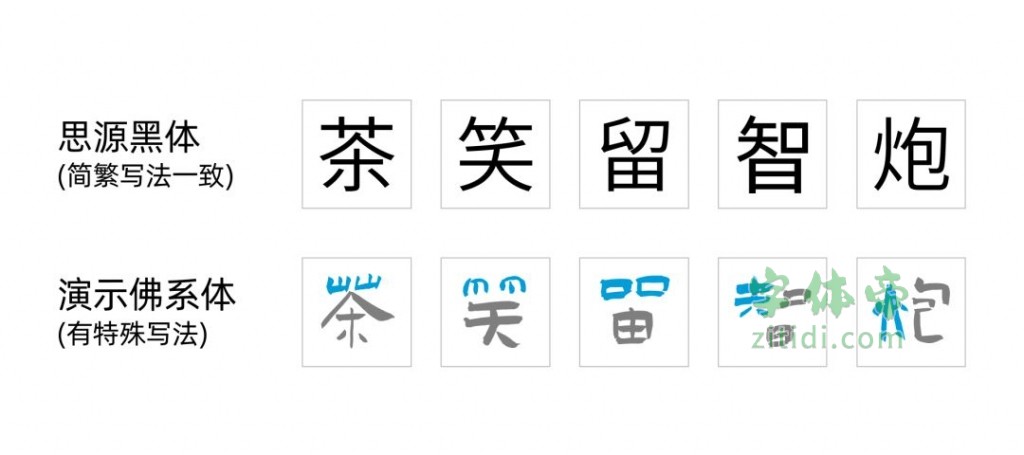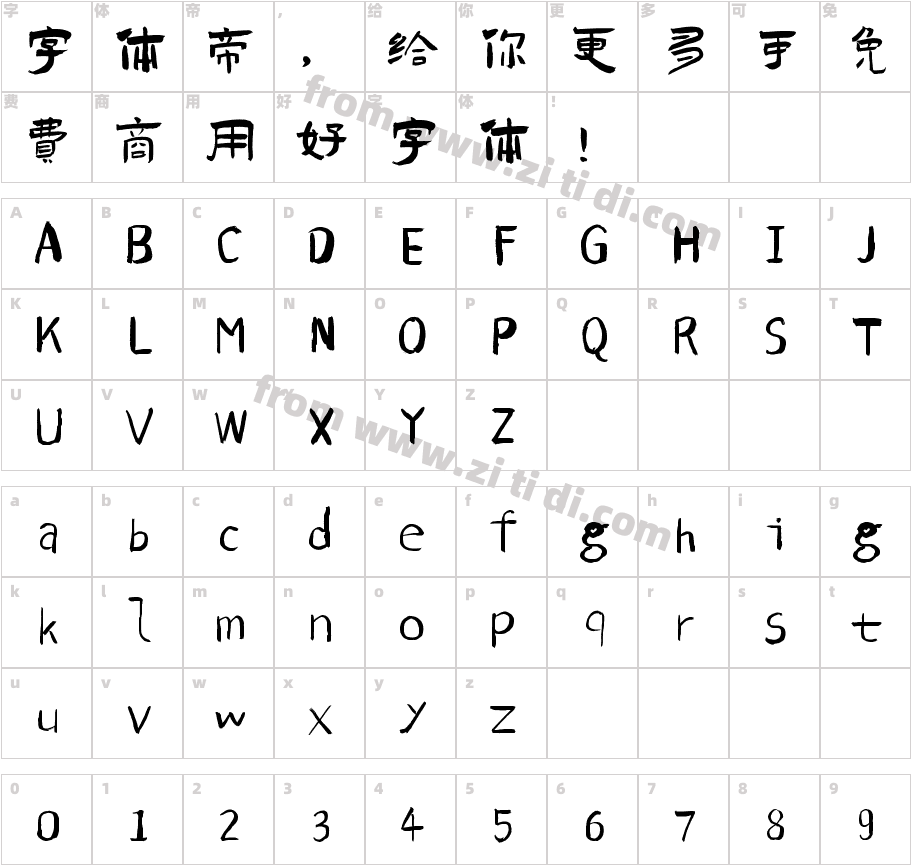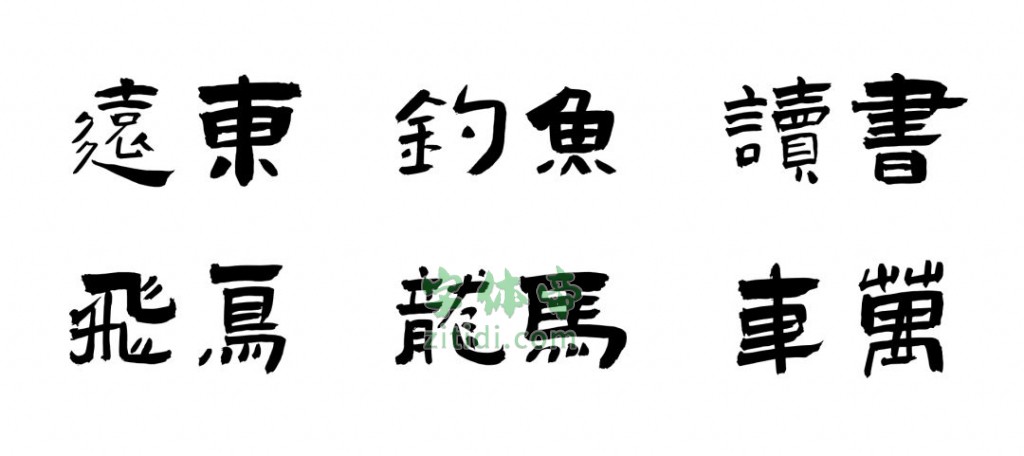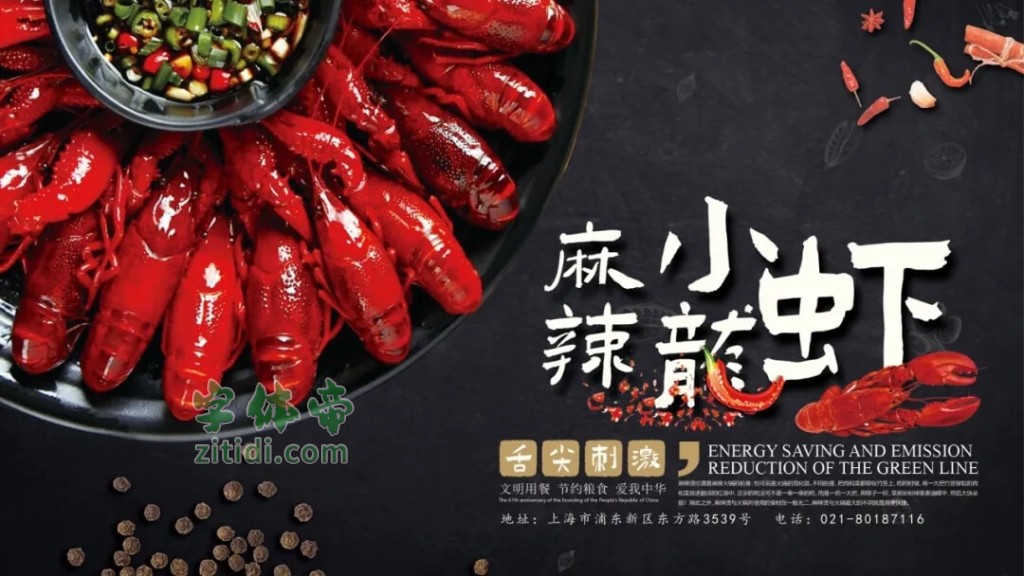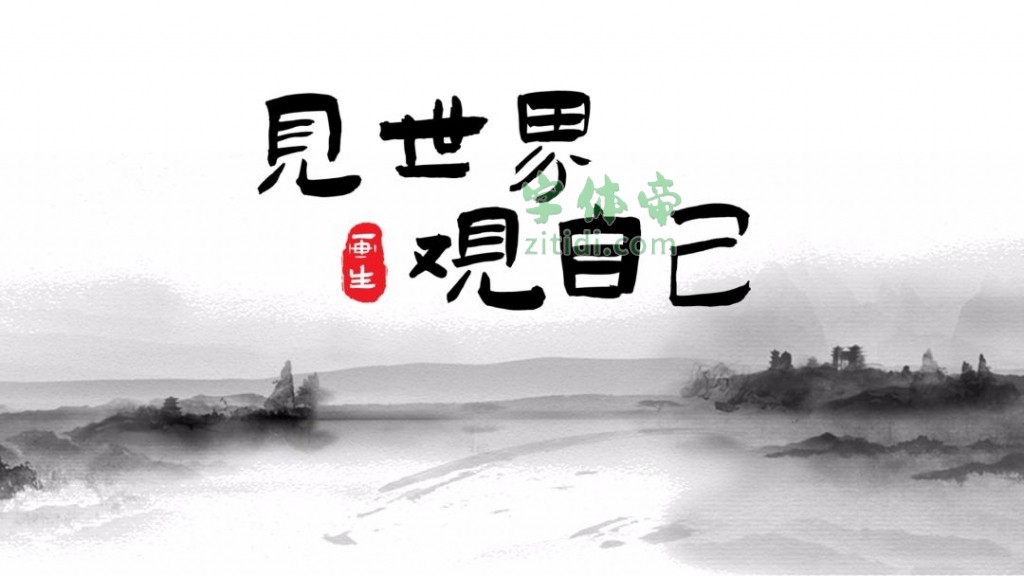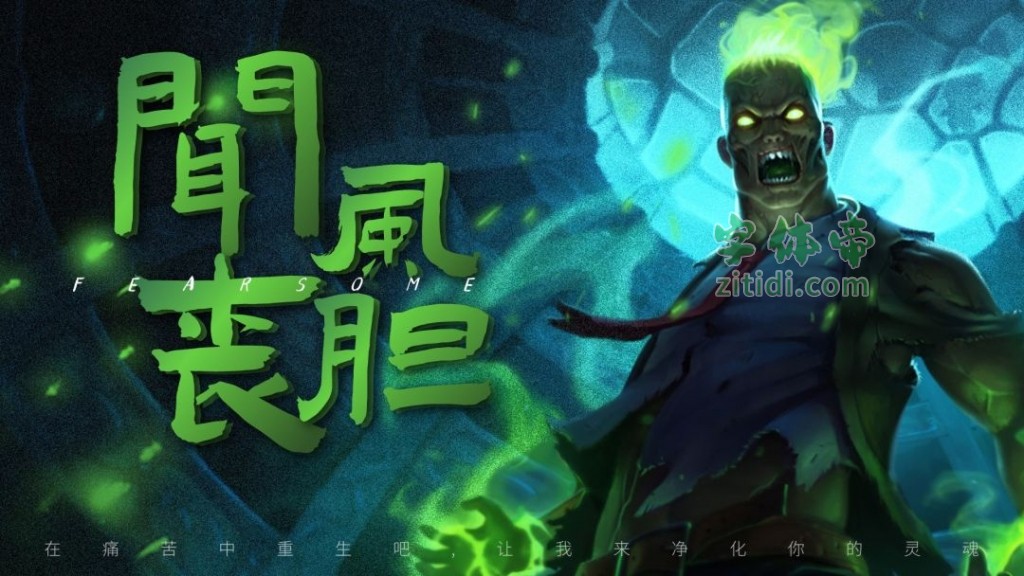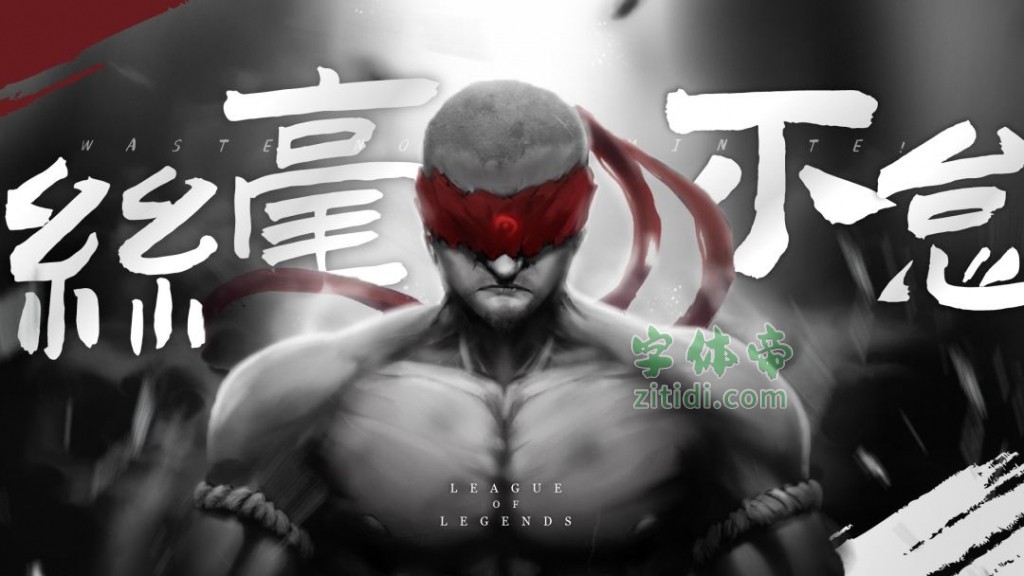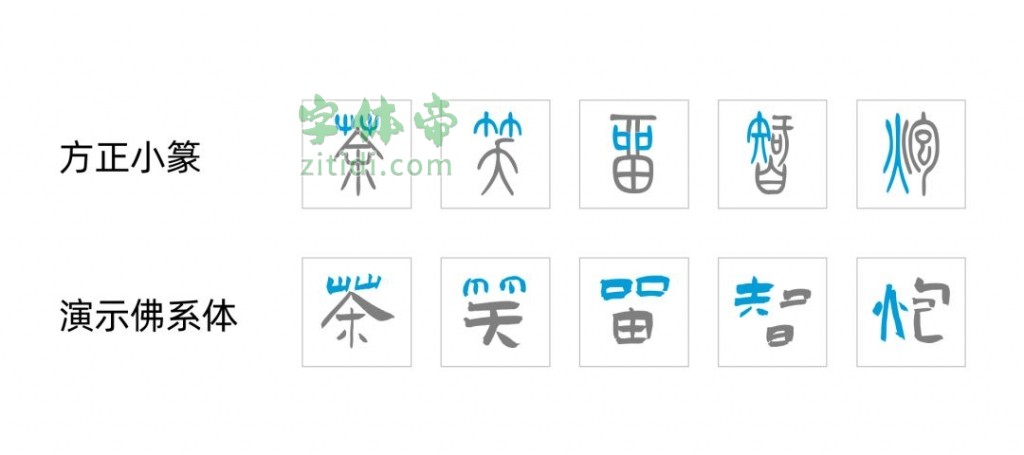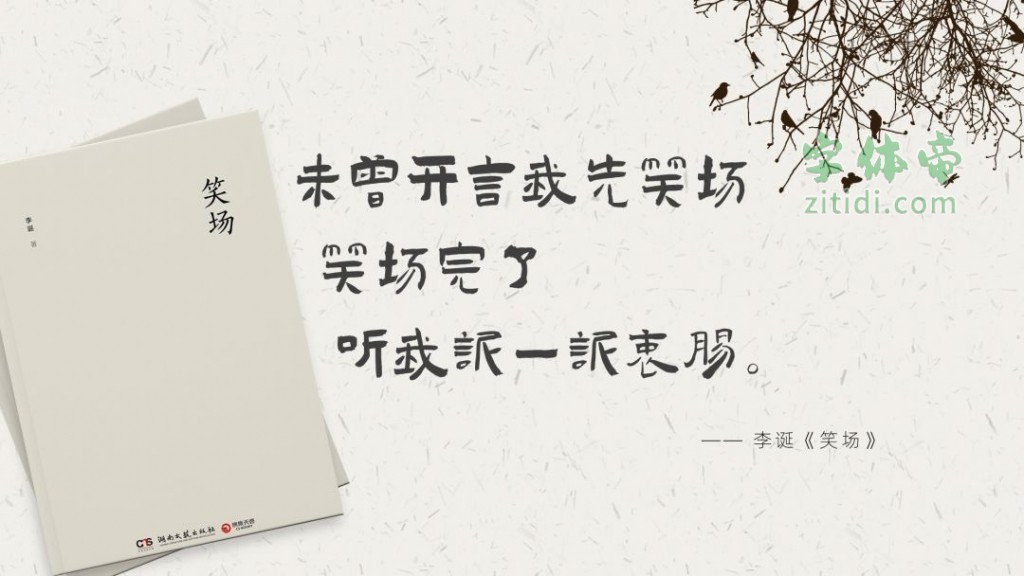
演示佛系体是一款风格十分特别的字体,纪国才老先生一生酷爱书法,在80岁这年亲手写了一套独具风格的字体,这套字体看似随意,但是蕴含着老先生一生的阅历和经验,随意之中又带点不随意。
字体整体乍看之下,似以繁体字为主。但多看一些,才发现,诸多奇特的偏旁部首写法,是现代简体繁体都不具备的。
一位练习书法多年的老先生,难道会标新立异自创写法吗? 实际恰好相反,我们需要到更加古老的字体中寻找答案——「演示佛系体」许多写法与小篆类似。
关于纪国才先生
出生于1939年的纪老先生,已过杖朝之年。一生经历了风云更迭,字如其人,印刻着时光的痕迹,沉淀着岁月的厚重,也诉说着人生的洒脱,有种超然物外之态。